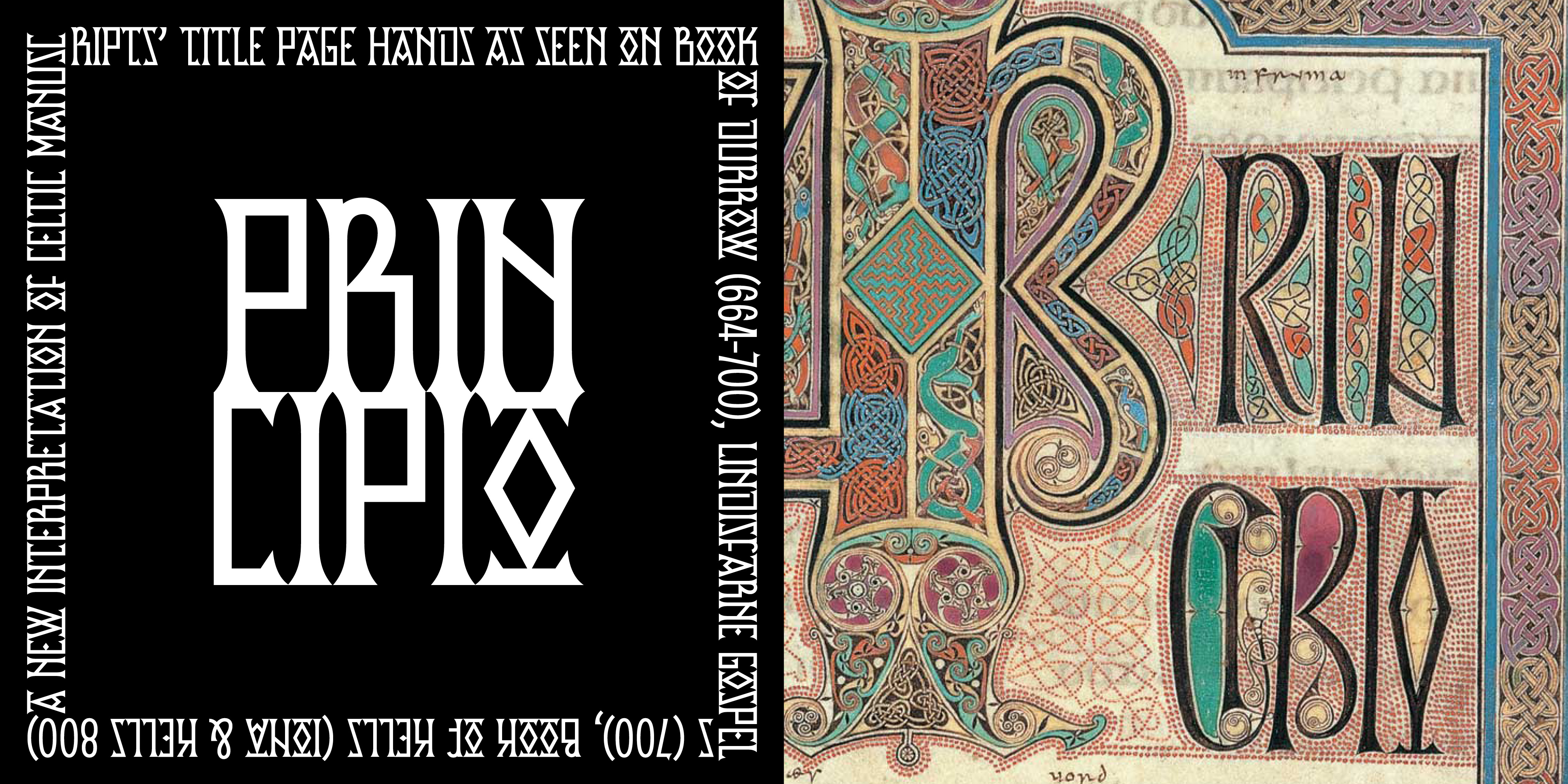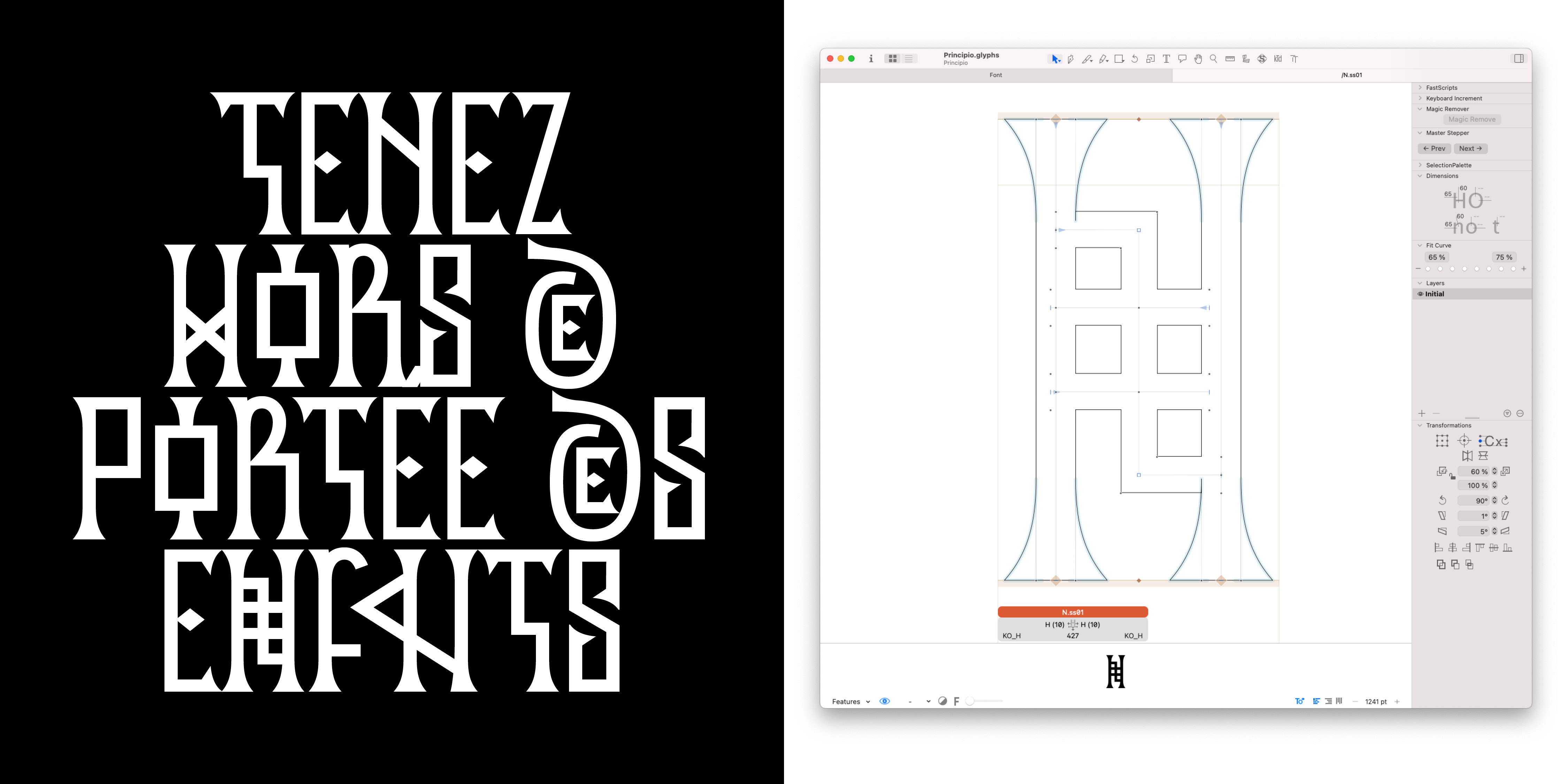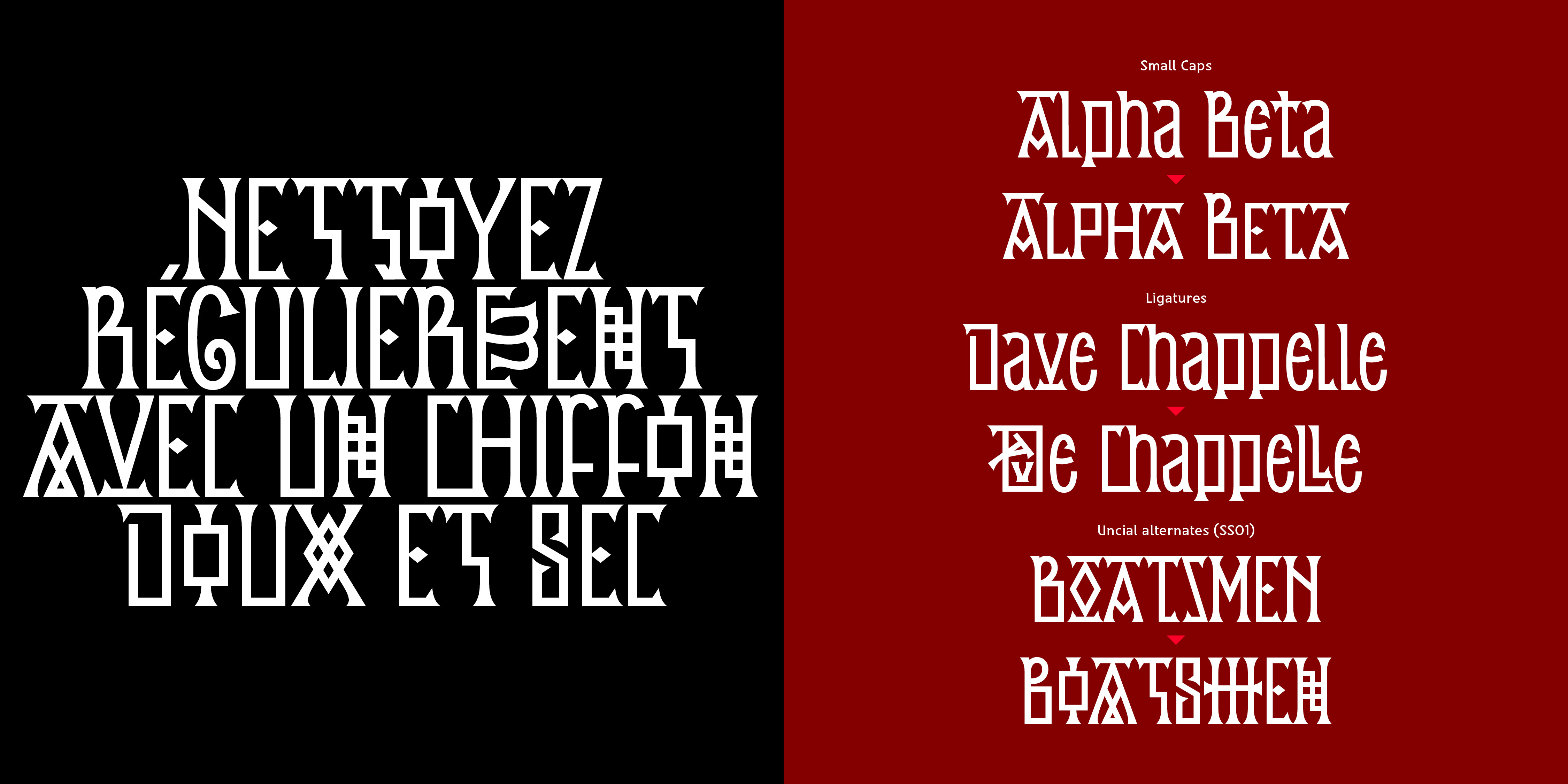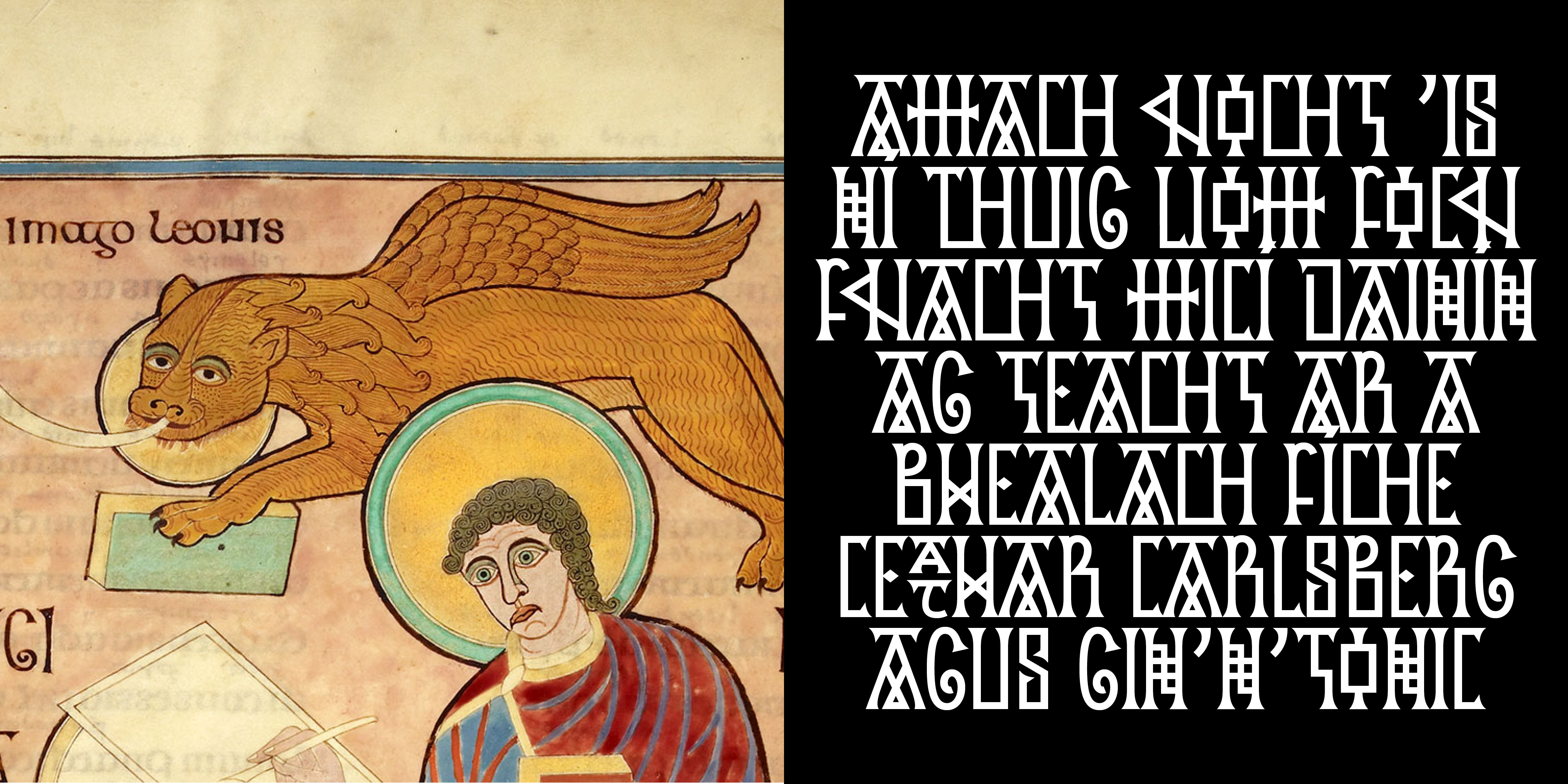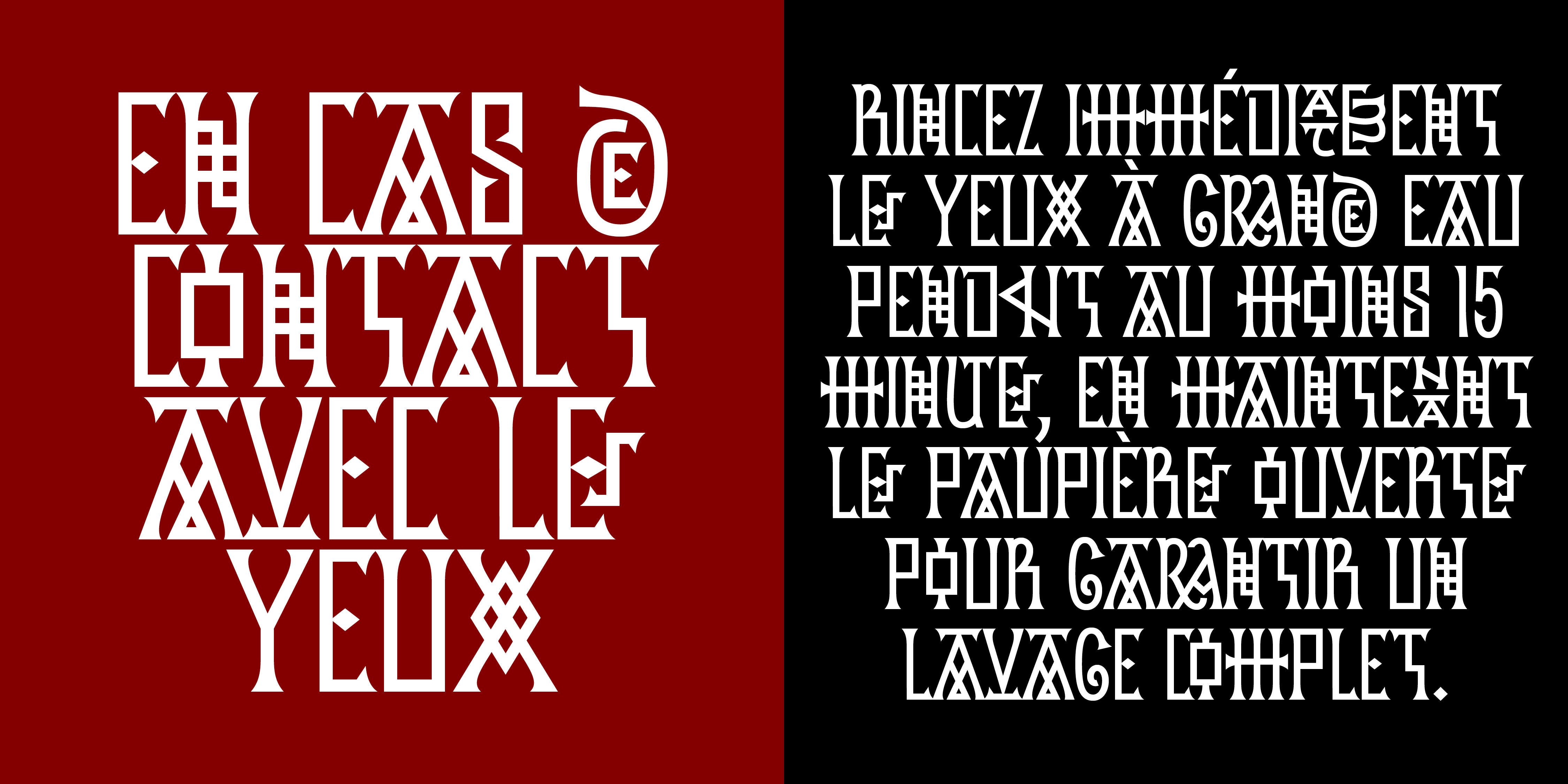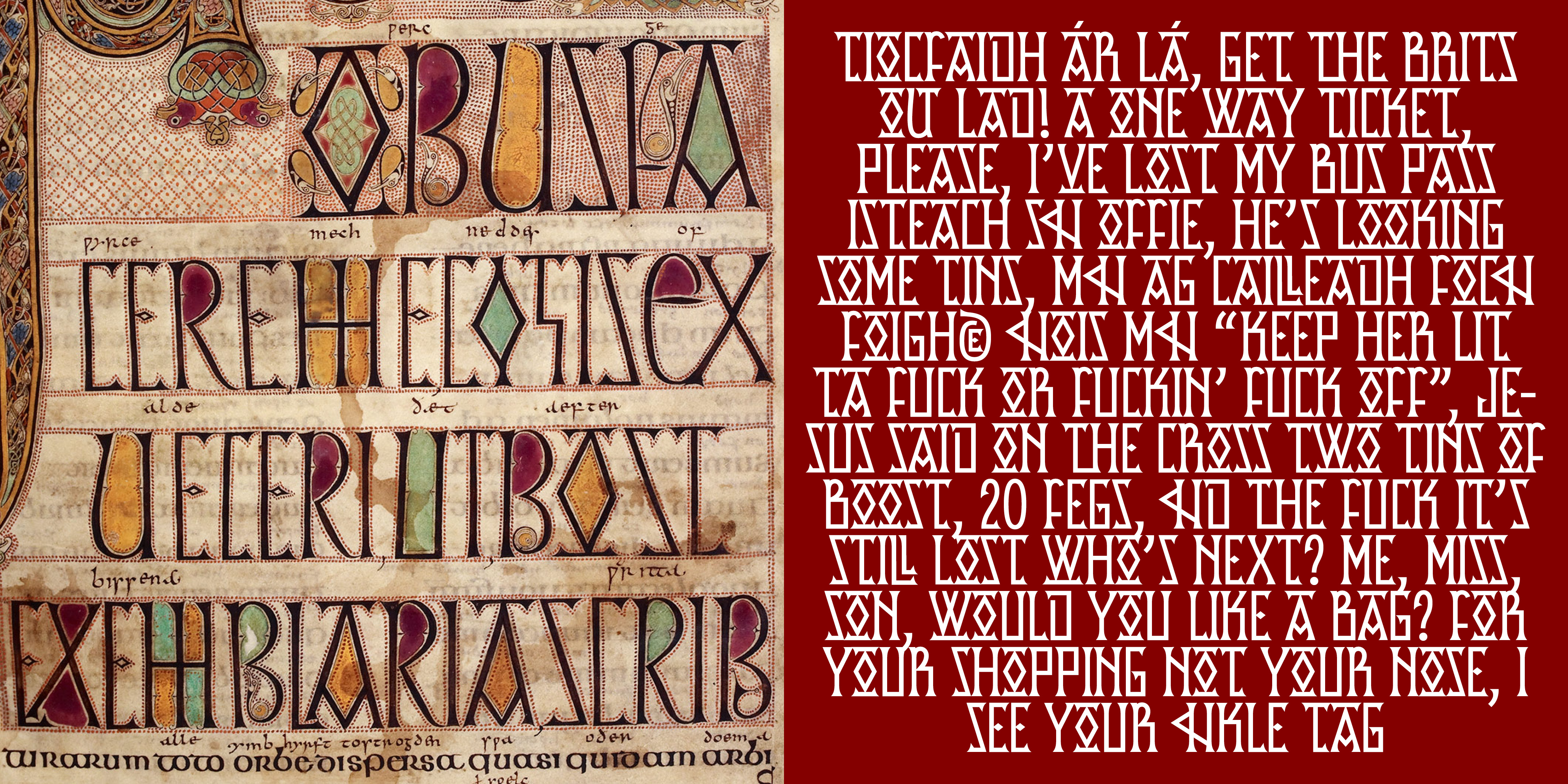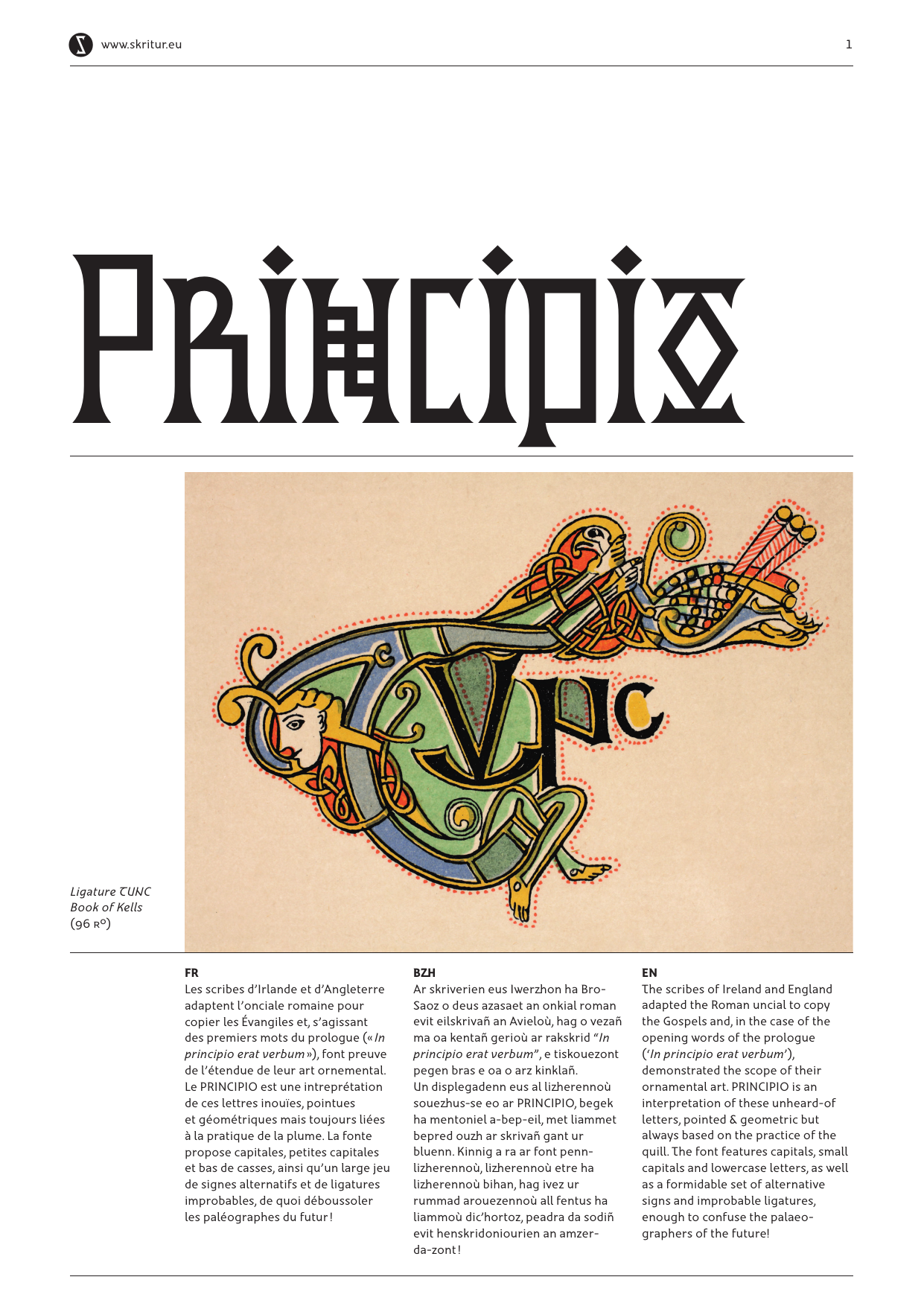
PRINCIPIO
Le Principio est une interprétation typographique libre des capitales que l’on observe sur les pages de titre des manuscrits enluminés irlandais et anglais à partir du VIIe siècle. Ces compositions typographiques aux caractères imbriqués et ornés sont d'une richesse graphique époustouflante. Parmi les plus beaux manuscrits qui nous sont parvenus figurent le Livre de Durrow (664–700), les Évangiles de Lindisfarne (700) et le Livre de Kells (Iona et Kells, 800). Le Principio tente de capturer l’esprit de l’art médiéval ancien dans une interprétation géométrique adaptée à une utilisation contemporaine. Les capitales, minuscules et petites capitales peuvent être utilisées séparément ou combinées pour créer une grande variété de tons et de styles. La typographie inclut également un large ensemble de ligatures complexes et d’alternatives onciales, offrant une riche diversité de formes à exploiter.
PRINCIPIO
Ar Principio zo un displegadur lizherennoù frank a weler war pajennoù titl dornskridoù sklêrijennet iwerzhonat ha saoznek adalek ar VIIvet kantved. Ar c'hompozadurioù tipografek-se gant arouezennoù neizhiet ha kinklet a zo pinvidik-kenañ war an anal. E-touez an dornskridoù gwellañ a chom bev emañ Levr Durrow (664–700), Avieloù Lindisfarne (700), ha Levr Kells (Iona ha Kells, 800). Klask a ra ar Principio tapout spered an arz kozh eus ar Grennamzer en un doare jedoniel dereat evit an implij a-vremañ. Ar lizherennoù bras, lizherennoù bihan ha lizherennoù bihan a c'hell bezañ implijet a-du pe a-gevret evit krouiñ ur bern tonioù ha stiloù. En tipografiezh e kaver ivez un toullad bras a liammoù kemplezh hag a stummoù all, ar pezh a ginnig ur bern stummoù da implijout.
PRINCIPIO
Principio is a free typographic interpretation of the capitals found on the title pages of illuminated Irish and English manuscripts dating back to the 7th century. These typographic compositions, with their interwoven and ornate characters, are of breathtaking graphic richness. Among the most beautiful manuscripts that have come down to us are the Book of Durrow (664–700), the Lindisfarne Gospels (700), and the Book of Kells (Iona and Kells, 800). Principio seeks to capture the spirit of early medieval art through a geometric interpretation adapted for contemporary use. Capitals, lowercase, and small caps can be used separately or combined to create a wide variety of tones and styles. The typeface also includes an extensive set of intricate ligatures and uncial alternates, offering a rich diversity of forms to explore.